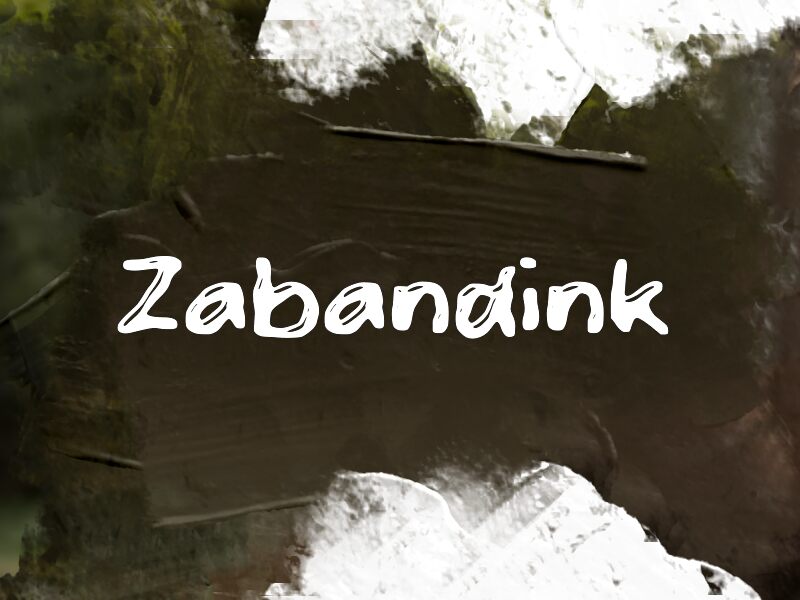
Zabandink od Wep to darmowy, ręcznie rysowany krój pisma typu display z wyrazistym, "atramentowym" charakterem pędzla i lekkim, kreskówkowym zacięciem. Litery sprawiają wrażenie odlanych, a nie skonstruowanych – z miękkimi wybrzuszeniami, obłymi łączeniami i drobnymi białymi nacięciami, które nadają tym masywnym kształtom życia.
Świetnie pasuje do tytułów plakatów, zinów, grafiki skejtowej lub streetwearowej, okładek książek dla dzieci, ulotek muzycznych i mocnych nagłówków w social mediach, gdzie ten darmowy font potrafi zdefiniować cały nastrój za pomocą zaledwie kilku słów. Użyj go do krótkich nagłówków, szkiców logo lub plansz tytułowych, gdy zależy Ci na literach, które wydają się szybkie, "mięsiste" i nieco niepokorne.
Zabandink
Prezentacja i próbka wizualna czcionki Zabandink